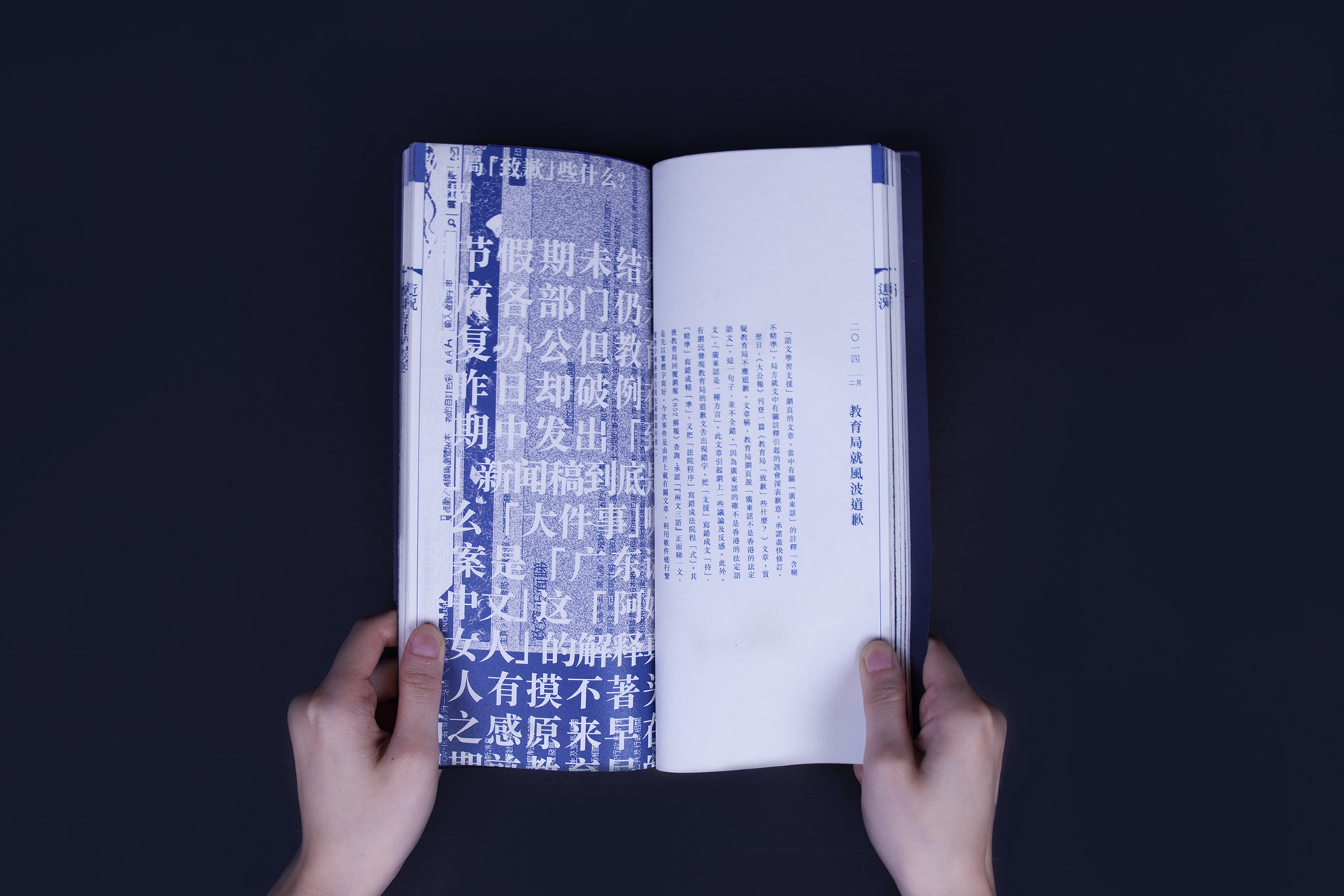
사라져가는 광둥어를 위한 디자인북
<THE VANISHING CANTONESE BOOK>은 ‘여기, 그리고 저기 – 현재, 그리고 미래’라는 프로젝트의 일환으로 출판된 디자인 서적이다.
이 프로젝트는 Poe Cheung이라는 홍콩의 디자이너가 시작했는데, 이 책을 통해 그녀는 광둥과 중국 남동부 지역에서 주로 사용되는 광둥어가 사라지는 이유에 대해 설명하고, 광둥어 기본 지식을 손쉽게 풀어서 담았다. 이를 통해 젊은세대들이 중국의 언어 문화에 대한 관심을 기울일 수 있도록 돕는다.
책의 디자인은 정보의 나열에 맞춰져 있는데, 광둥어에 대한 복잡한 정보와 표준 중국어의 공식 표기법 등이 감각적으로 배열되어 있어 디자인적으로도 매우 훌륭하다.